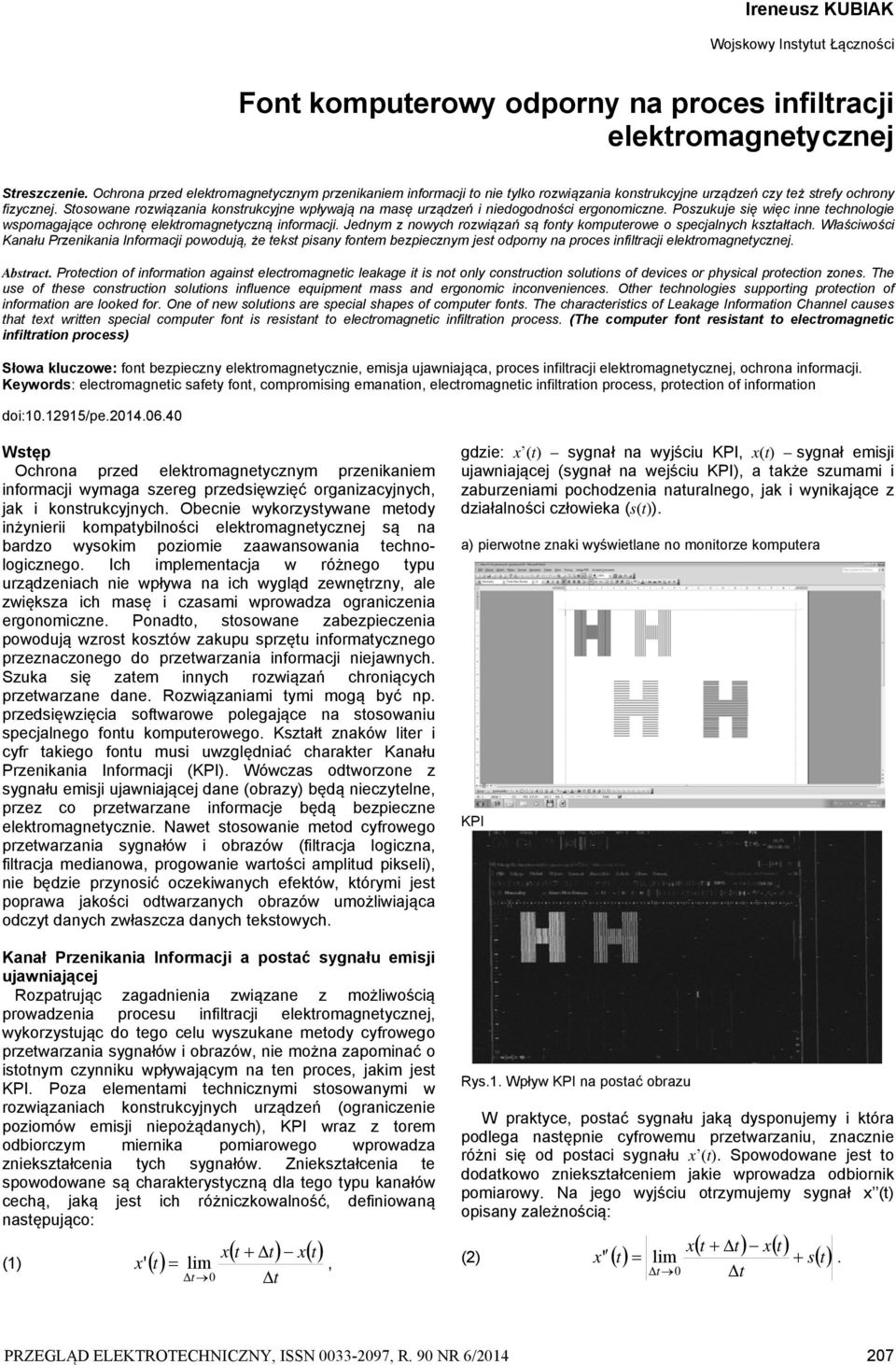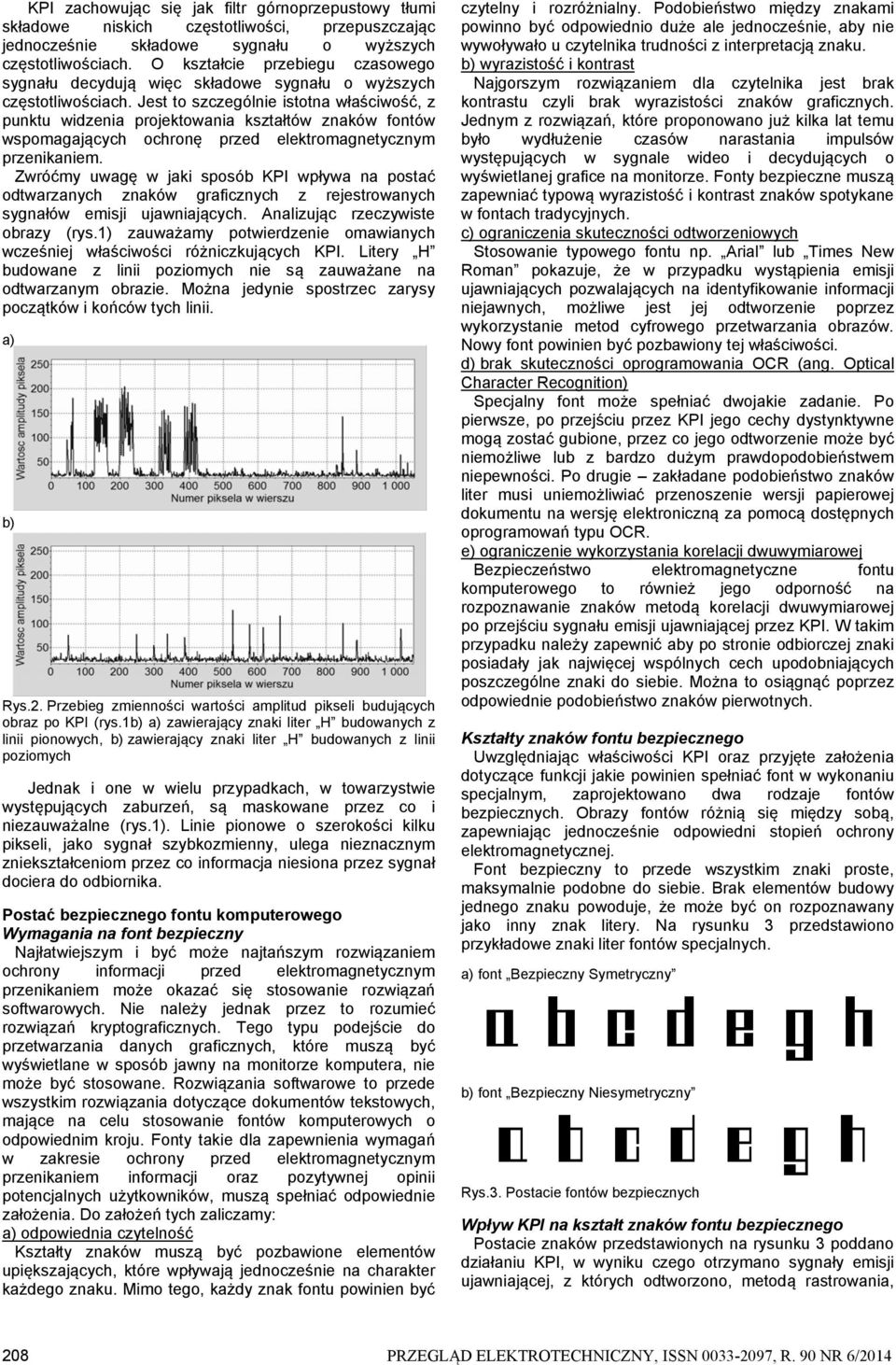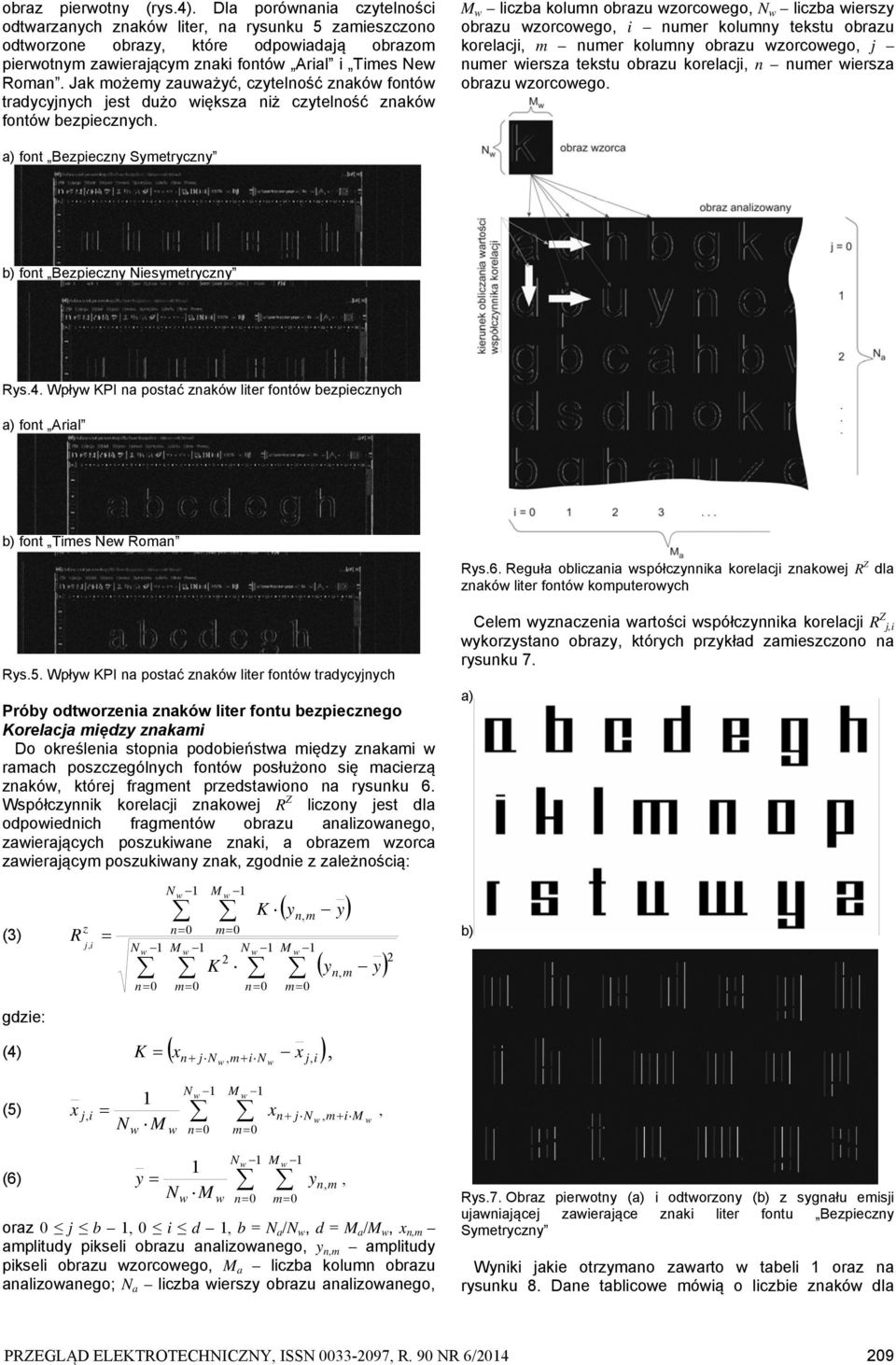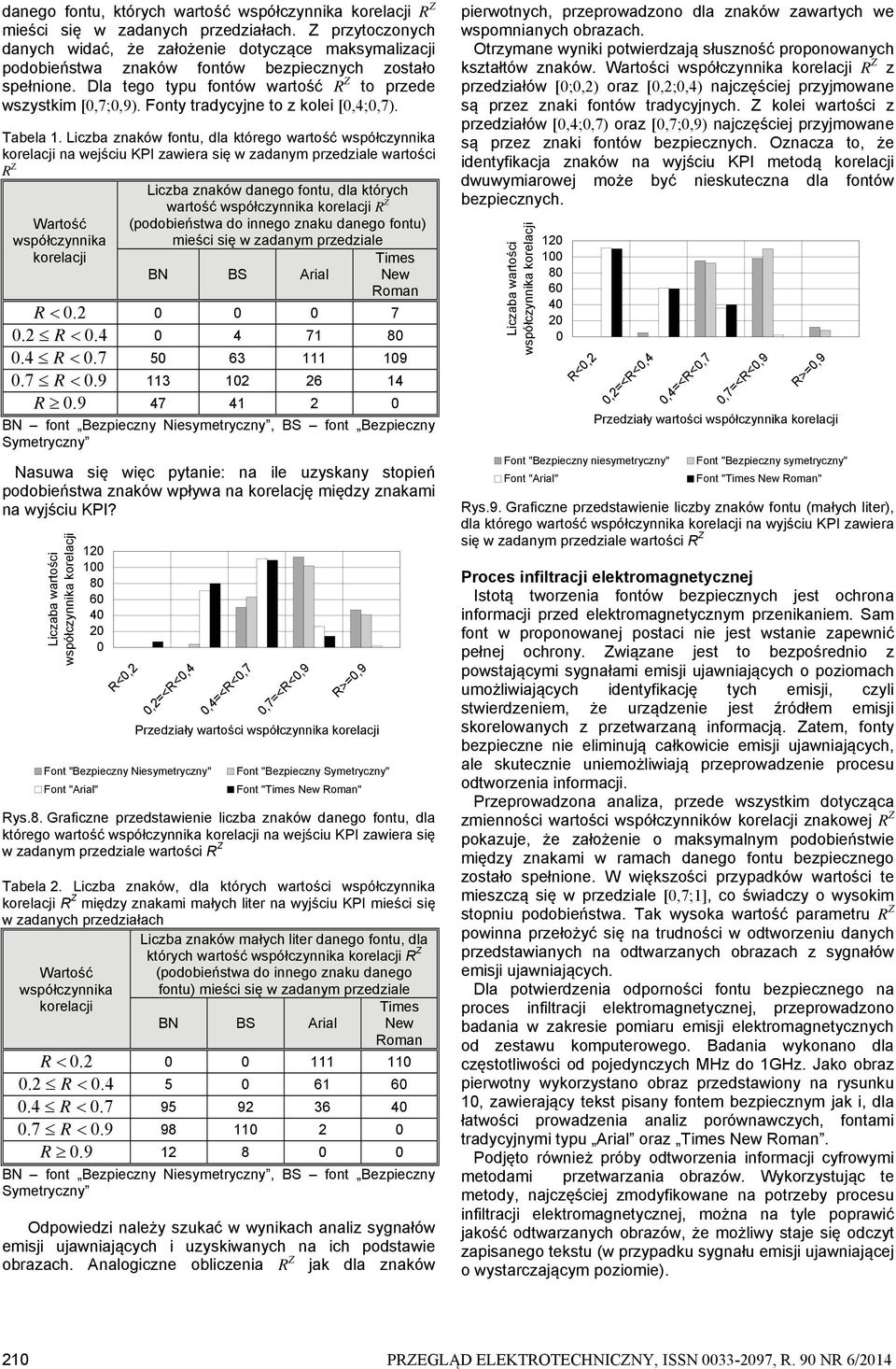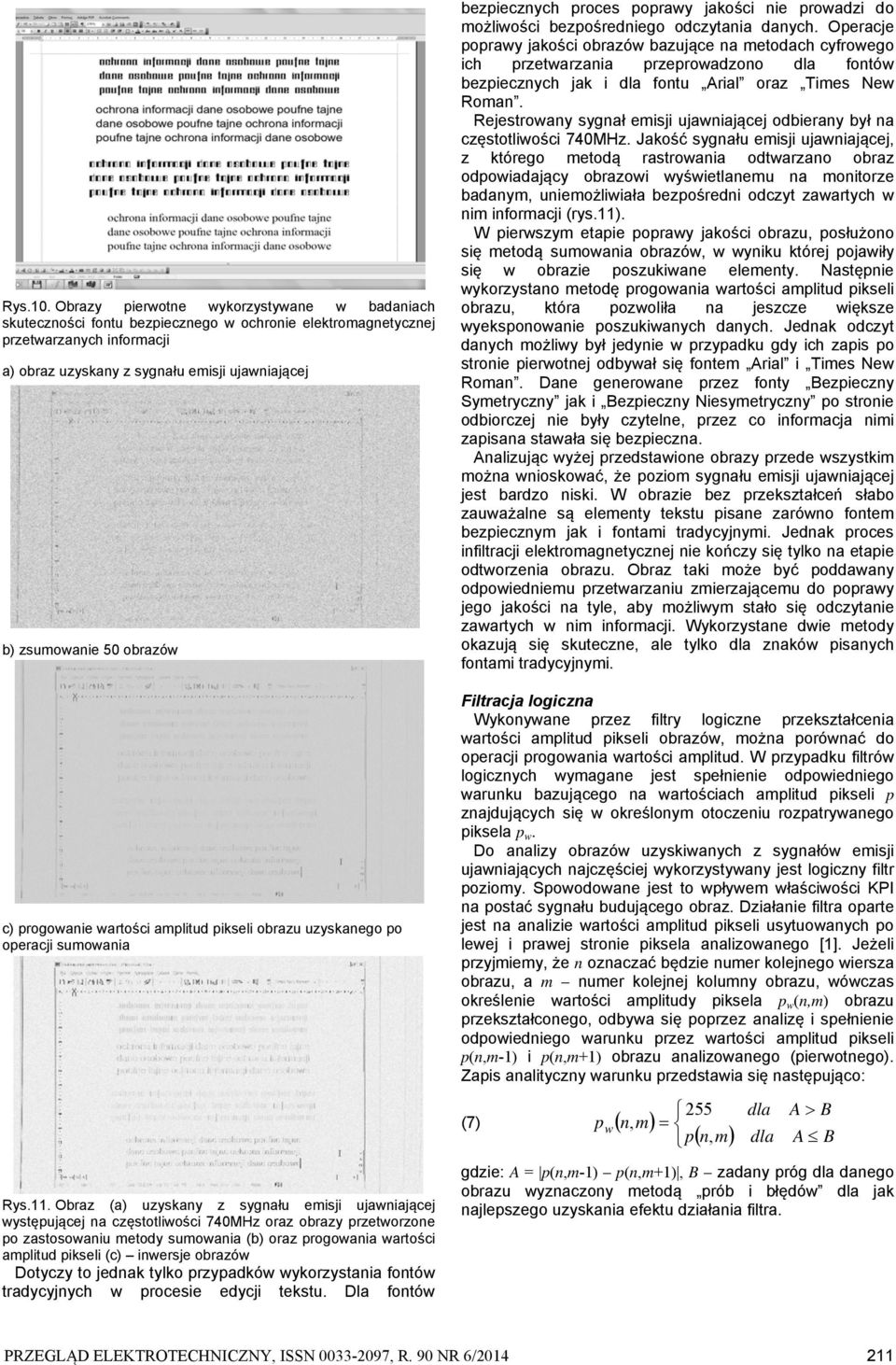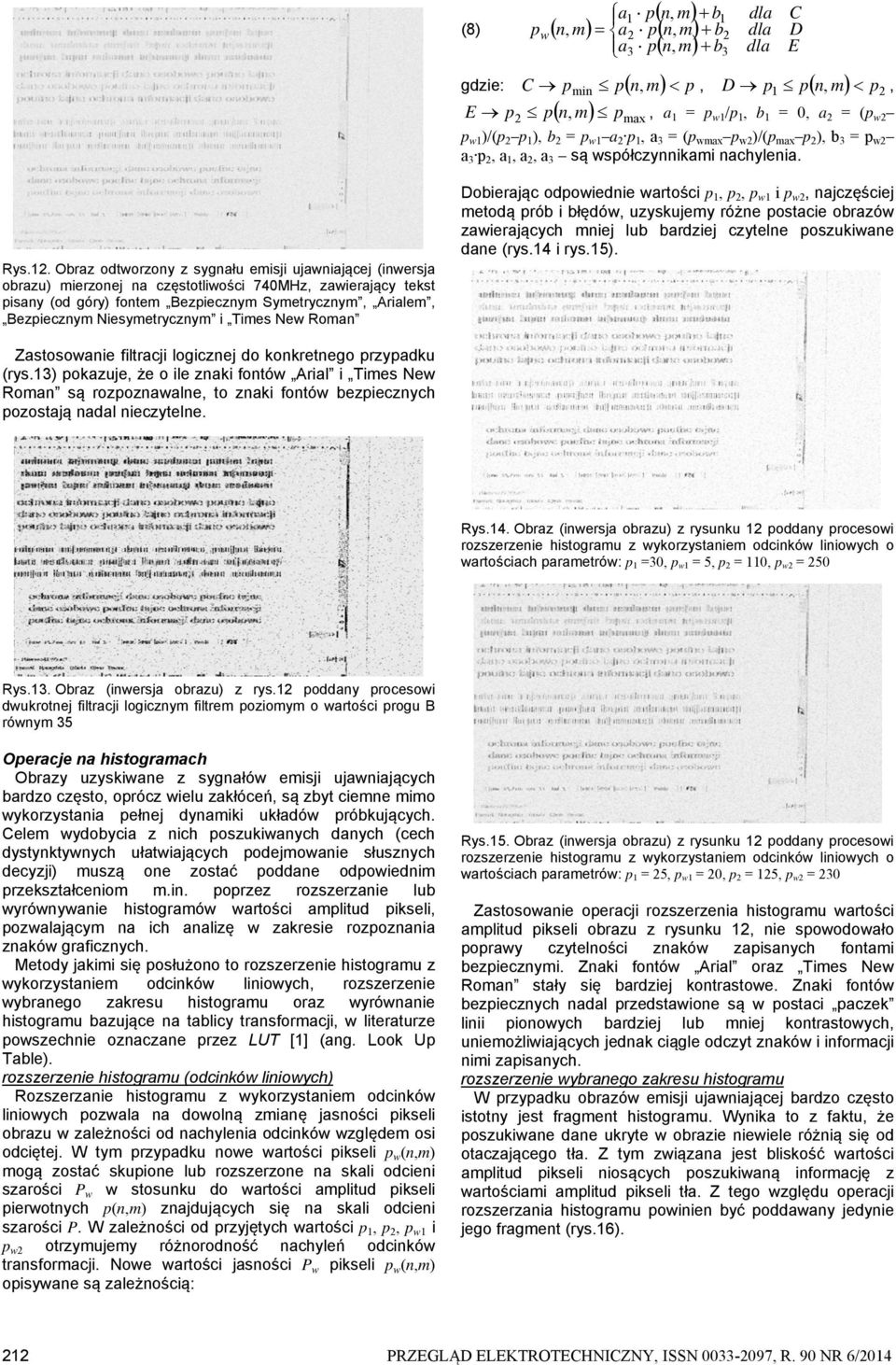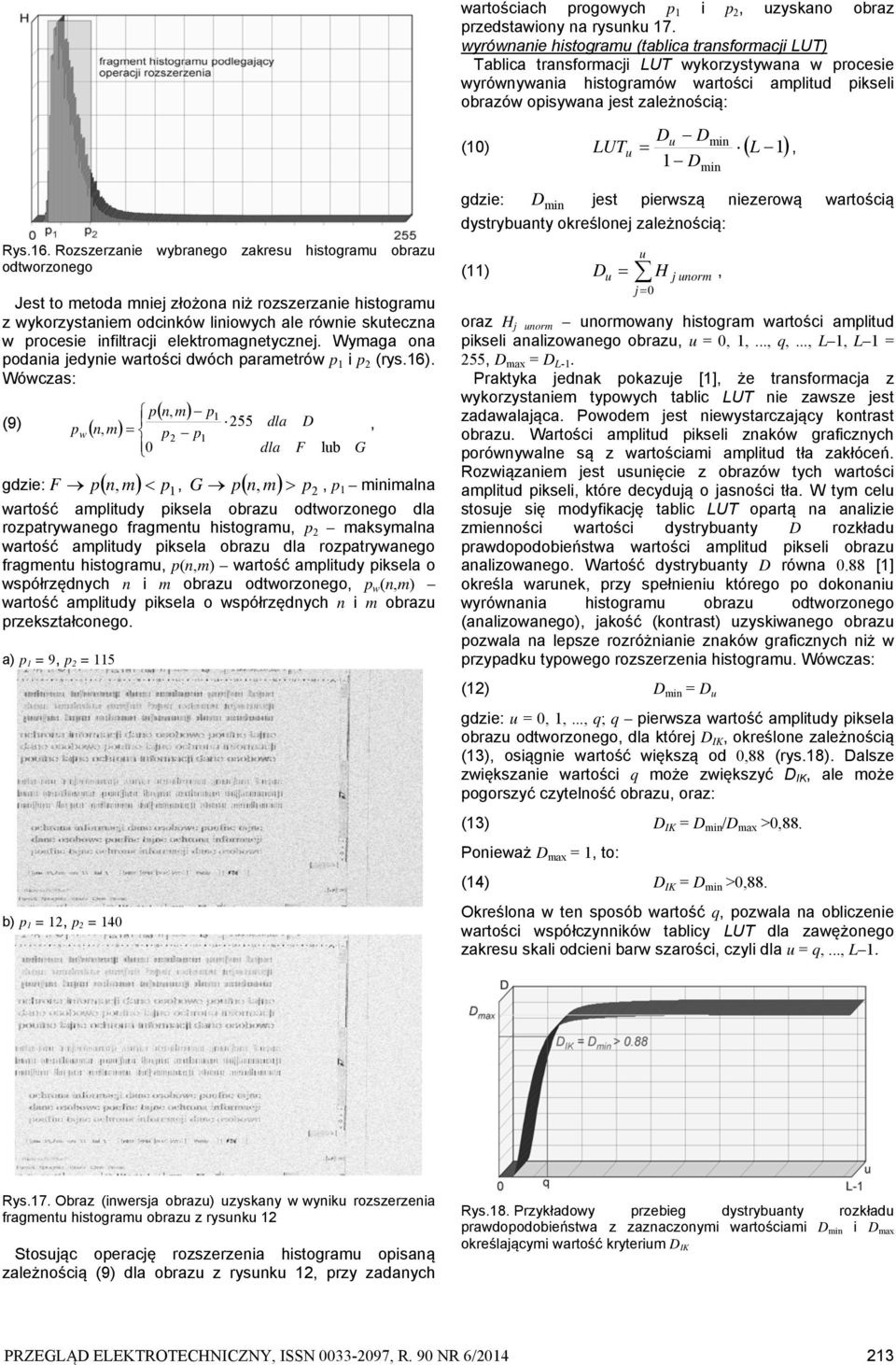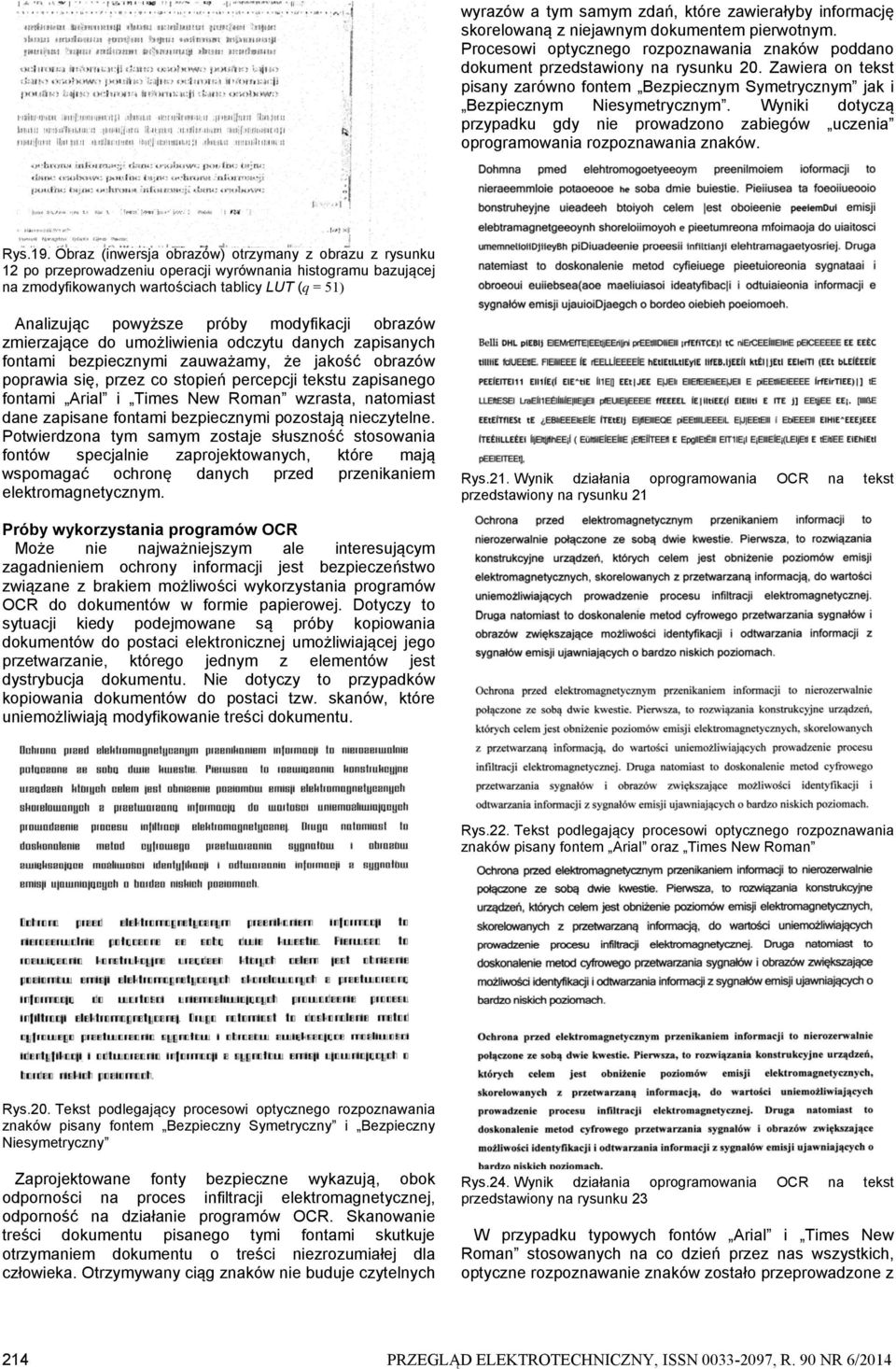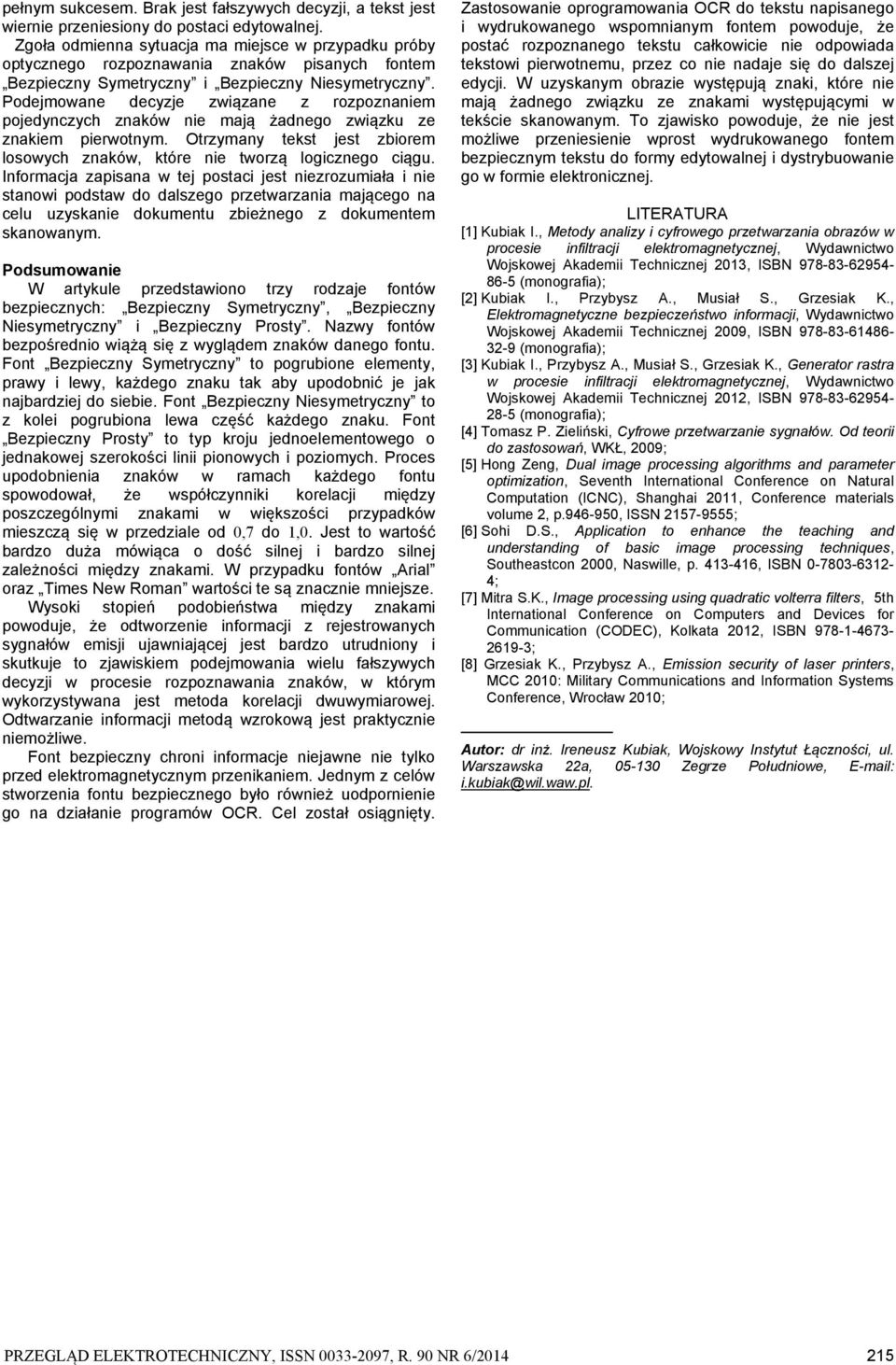
Font komputerowy odporny na proces infiltracji elektromagnetycznej
1 Ireneusz KUBIAK Wojskoy Instytut Łączności Font komputeroy odporny na proces infiltracji elektromagnetycznej Streszczenie. Ochrona przed elektromagnetycznym przenikaniem informacji to nie tylko roziązania konstrukcyjne urządzeń czy też strefy ochrony fizycznej. Stosoane roziązania konstrukcyjne płyają na masę urządzeń i niedogodności ergonomiczne. Poszukuje się ięc inne technologie spomagające ochronę elektromagnetyczną informacji. Jednym z noych roziązań są fonty komputeroe o specjalnych kształtach. Właściości Kanału Przenikania Informacji poodują że tekst pisany fontem bezpiecznym jest odporny na proces infiltracji elektromagnetycznej. Abstract. Protection of information against electromagnetic leakage it is not only construction solutions of devices or physical protection zones. The use of these construction solutions influence equipment mass and ergonomic inconveniences. Other technologies supporting protection of information are looked for. One of ne solutions are special shapes of computer fonts. The characteristics of Leakage Information Channel causes that text ritten special computer font is resistant to electromagnetic infiltration process. (The computer font resistant to electromagnetic infiltration process) Słoa kluczoe: font bezpieczny elektromagnetycznie emisja ujaniająca proces infiltracji elektromagnetycznej ochrona informacji. Keyords: electromagnetic safety font compromising emanation electromagnetic infiltration process protection of information doi: /pe Wstęp Ochrona przed elektromagnetycznym przenikaniem informacji ymaga szereg przedsięzięć organizacyjnych jak i konstrukcyjnych. Obecnie ykorzystyane metody inżynierii kompatybilności elektromagnetycznej są na bardzo ysokim poziomie zaaansoania technologicznego. Ich implementacja różnego typu urządzeniach nie płya na ich ygląd zenętrzny ale ziększa ich masę i czasami proadza ograniczenia ergonomiczne. Ponadto stosoane zabezpieczenia poodują zrost kosztó zakupu sprzętu informatycznego przeznaczonego do przetarzania informacji niejanych. Szuka się zatem innych roziązań chroniących przetarzane dane. Roziązaniami tymi mogą być np. przedsięzięcia softaroe polegające na stosoaniu specjalnego fontu komputeroego. Kształt znakó liter i cyfr takiego fontu musi uzględniać charakter Kanału Przenikania Informacji (KPI). Wóczas odtorzone z sygnału emisji ujaniającej dane (obrazy) będą nieczytelne przez co przetarzane informacje będą bezpieczne elektromagnetycznie. Naet stosoanie metod cyfroego przetarzania sygnałó i obrazó (filtracja logiczna filtracja medianoa progoanie artości amplitud pikseli) nie będzie przynosić oczekianych efektó którymi jest popraa jakości odtarzanych obrazó umożliiająca odczyt danych złaszcza danych tekstoych. Kanał Przenikania Informacji a postać sygnału emisji ujaniającej Rozpatrując zagadnienia ziązane z możliością proadzenia procesu infiltracji elektromagnetycznej ykorzystując do tego celu yszukane metody cyfroego przetarzania sygnałó i obrazó nie można zapominać o istotnym czynniku płyającym na ten proces jakim jest KPI. Poza elementami technicznymi stosoanymi roziązaniach konstrukcyjnych urządzeń (ograniczenie poziomó emisji niepożądanych) KPI raz z torem odbiorczym miernika pomiaroego proadza zniekształcenia tych sygnałó. Zniekształcenia te spoodoane są charakterystyczną tego typu kanałó cechą jaką jest ich różniczkoalność definioaną następująco: x (1) t t xt x' t lim t 0 t gdzie: x (t) sygnał na yjściu KPI x(t) sygnał emisji ujaniającej (sygnał na ejściu KPI) a także szumami i zaburzeniami pochodzenia naturalnego jak i ynikające z działalności człoieka (s(t)). a) pierotne znaki yśietlane no monitorze komputera b) obraz uzyskany z sygnału emisji ujaniającej po przejściu przez KPI Rys.1. Wpły KPI na postać obrazu W praktyce postać sygnału jaką dysponujemy i która podlega następnie cyfroemu przetarzaniu znacznie różni się od postaci sygnału x (t). Spoodoane jest to dodatkoo zniekształceniem jakie proadza odbiornik pomiaroy. Na jego yjściu otrzymujemy sygnał x (t) opisany zależnością: x (2) t t xt x' t lim s t. t 0 t PRZEGLĄD ELEKTROTECHNICZNY ISSN R. 90 NR 6/
2 KPI zachoując się jak filtr górnoprzepustoy tłumi składoe niskich częstotliości przepuszczając jednocześnie składoe sygnału o yższych częstotliościach. O kształcie przebiegu czasoego sygnału decydują ięc składoe sygnału o yższych częstotliościach. Jest to szczególnie istotna łaściość z punktu idzenia projektoania kształtó znakó fontó spomagających ochronę przed elektromagnetycznym przenikaniem. Zróćmy uagę jaki sposób KPI płya na postać odtarzanych znakó graficznych z rejestroanych sygnałó emisji ujaniających. Analizując rzeczyiste obrazy (rys.1) zauażamy potierdzenie omaianych cześniej łaściości różniczkujących KPI. Litery H budoane z linii poziomych nie są zauażane na odtarzanym obrazie. Można jedynie spostrzec zarysy początkó i końcó tych linii. a) b) Rys.2. Przebieg zmienności artości amplitud pikseli budujących obraz po KPI (rys.1b) a) zaierający znaki liter H budoanych z linii pionoych b) zaierający znaki liter H budoanych z linii poziomych Jednak i one ielu przypadkach toarzystie ystępujących zaburzeń są maskoane przez co i niezauażalne (rys.1). Linie pionoe o szerokości kilku pikseli jako sygnał szybkozmienny ulega nieznacznym zniekształceniom przez co informacja niesiona przez sygnał dociera do odbiornika. Postać bezpiecznego fontu komputeroego Wymagania na font bezpieczny Najłatiejszym i być może najtańszym roziązaniem ochrony informacji przed elektromagnetycznym przenikaniem może okazać się stosoanie roziązań softaroych. Nie należy jednak przez to rozumieć roziązań kryptograficznych. Tego typu podejście do przetarzania danych graficznych które muszą być yśietlane sposób jany na monitorze komputera nie może być stosoane. Roziązania softaroe to przede szystkim roziązania dotyczące dokumentó tekstoych mające na celu stosoanie fontó komputeroych o odpoiednim kroju. Fonty takie zapenienia ymagań zakresie ochrony przed elektromagnetycznym przenikaniem informacji oraz pozytynej opinii potencjalnych użytkonikó muszą spełniać odpoiednie założenia. Do założeń tych zaliczamy: a) odpoiednia czytelność Kształty znakó muszą być pozbaione elementó upiększających które płyają jednocześnie na charakter każdego znaku. Mimo tego każdy znak fontu poinien być czytelny i rozróżnialny. Podobieństo między znakami poinno być odpoiednio duże ale jednocześnie aby nie yołyało u czytelnika trudności z interpretacją znaku. b) yrazistość i kontrast Najgorszym roziązaniem czytelnika jest brak kontrastu czyli brak yrazistości znakó graficznych. Jednym z roziązań które proponoano już kilka lat temu było ydłużenie czasó narastania impulsó ystępujących sygnale ideo i decydujących o yśietlanej grafice na monitorze. Fonty bezpieczne muszą zapeniać typoą yrazistość i kontrast znakó spotykane fontach tradycyjnych. c) ograniczenia skuteczności odtorzenioych Stosoanie typoego fontu np. Arial lub Times Ne Roman pokazuje że przypadku ystąpienia emisji ujaniających pozalających na identyfikoanie informacji niejanych możlie jest jej odtorzenie poprzez ykorzystanie metod cyfroego przetarzania obrazó. Noy font poinien być pozbaiony tej łaściości. d) brak skuteczności oprogramoania OCR (ang. Optical Character Recognition) Specjalny font może spełniać dojakie zadanie. Po piersze po przejściu przez KPI jego cechy dystynktyne mogą zostać gubione przez co jego odtorzenie może być niemożlie lub z bardzo dużym pradopodobieństem niepeności. Po drugie zakładane podobieństo znakó liter musi uniemożliiać przenoszenie ersji papieroej dokumentu na ersję elektroniczną za pomocą dostępnych oprogramoań typu OCR. e) ograniczenie ykorzystania korelacji duymiaroej Bezpieczeństo elektromagnetyczne fontu komputeroego to rónież jego odporność na rozpoznaanie znakó metodą korelacji duymiaroej po przejściu sygnału emisji ujaniającej przez KPI. W takim przypadku należy zapenić aby po stronie odbiorczej znaki posiadały jak najięcej spólnych cech upodobniających poszczególne znaki do siebie. Można to osiągnąć poprzez odpoiednie podobieństo znakó pierotnych. Kształty znakó fontu bezpiecznego Uzględniając łaściości KPI oraz przyjęte założenia dotyczące funkcji jakie poinien spełniać font ykonaniu specjalnym zaprojektoano da rodzaje fontó bezpiecznych. Obrazy fontó różnią się między sobą zapeniając jednocześnie odpoiedni stopień ochrony elektromagnetycznej. Font bezpieczny to przede szystkim znaki proste maksymalnie podobne do siebie. Brak elementó budoy jednego znaku pooduje że może być on rozpoznaany jako inny znak litery. Na rysunku 3 przedstaiono przykładoe znaki liter fontó specjalnych. a) font Bezpieczny Symetryczny b) font Bezpieczny Niesymetryczny Rys.3. Postacie fontó bezpiecznych Wpły KPI na kształt znakó fontu bezpiecznego Postacie znakó przedstaionych na rysunku 3 poddano działaniu KPI yniku czego otrzymano sygnały emisji ujaniającej z których odtorzono metodą rastroania 208 PRZEGLĄD ELEKTROTECHNICZNY ISSN R. 90 NR 6/2014
3 obraz pierotny (rys.4). Dla porónania czytelności odtarzanych znakó liter na rysunku 5 zamieszczono odtorzone obrazy które odpoiadają obrazom pierotnym zaierającym znaki fontó Arial i Times Ne Roman. Jak możemy zauażyć czytelność znakó fontó tradycyjnych jest dużo iększa niż czytelność znakó fontó bezpiecznych. M liczba kolumn obrazu zorcoego N liczba ierszy obrazu zorcoego i numer kolumny tekstu obrazu korelacji m numer kolumny obrazu zorcoego j numer iersza tekstu obrazu korelacji n numer iersza obrazu zorcoego. a) font Bezpieczny Symetryczny b) font Bezpieczny Niesymetryczny Rys.4. Wpły KPI na postać znakó liter fontó bezpiecznych a) font Arial b) font Times Ne Roman Rys.6. Reguła obliczania spółczynnika korelacji znakoej R Z znakó liter fontó komputeroych Rys.5. Wpły KPI na postać znakó liter fontó tradycyjnych Próby odtorzenia znakó liter fontu bezpiecznego Korelacja między znakami Do określenia stopnia podobieństa między znakami ramach poszczególnych fontó posłużono się macierzą znakó której fragment przedstaiono na rysunku 6. Współczynnik korelacji znakoej R Z liczony jest odpoiednich fragmentó obrazu analizoanego zaierających poszukiane znaki a obrazem zorca zaierającym poszukiany znak zgodnie z zależnością: (3) R z j i n0 N 1 n0 N 1 M 1 m0 M 1 n0 n m m0 2 N 1 M 1 K K y m0 y y n m y 2 Celem yznaczenia artości spółczynnika korelacji R Z ji ykorzystano obrazy których przykład zamieszczono na rysunku 7. a) b) gdzie: (4) K x n x (5) j i jn min j i N 1 M 1 1 x xn jn mim N M n0 m0 N 1 M 1 1 (6) y yn m N M n0 m0 oraz 0 j b 1 0 i d 1 b = N a /N d = M a /M x nm amplitudy pikseli obrazu analizoanego y nm amplitudy pikseli obrazu zorcoego M a liczba kolumn obrazu analizoanego; N a liczba ierszy obrazu analizoanego Rys.7. Obraz pierotny (a) i odtorzony (b) z sygnału emisji ujaniającej zaierające znaki liter fontu Bezpieczny Symetryczny Wyniki jakie otrzymano zaarto tabeli 1 oraz na rysunku 8. Dane tablicoe móią o liczbie znakó PRZEGLĄD ELEKTROTECHNICZNY ISSN R. 90 NR 6/
4 danego fontu których artość spółczynnika korelacji R Z mieści się zadanych przedziałach. Z przytoczonych danych idać że założenie dotyczące maksymalizacji podobieństa znakó fontó bezpiecznych zostało spełnione. Dla tego typu fontó artość R Z to przede szystkim [07;09). Fonty tradycyjne to z kolei [04;07). Tabela 1. Liczba znakó fontu którego artość spółczynnika korelacji na ejściu KPI zaiera się zadanym przedziale artości R Z Wartość spółczynnika korelacji Liczba znakó danego fontu których artość spółczynnika korelacji R Z (podobieństa do innego znaku danego fontu) mieści się zadanym przedziale Times BN BS Arial Ne Roman R R R R R BN font Bezpieczny Niesymetryczny BS font Bezpieczny Symetryczny Nasua się ięc pytanie: na ile uzyskany stopień podobieństa znakó płya na korelację między znakami na yjściu KPI? Liczaba artości spółczynnika korelacji R<02 02=<R<04 Font "Bezpieczny Niesymetryczny" Font "Arial" 04=<R<07 07=<R<09 R>=09 Przedziały artości spółczynnika korelacji Font "Bezpieczny Symetryczny" Font "Times Ne Roman" Rys.8. Graficzne przedstaienie liczba znakó danego fontu którego artość spółczynnika korelacji na ejściu KPI zaiera się zadanym przedziale artości R Z Tabela 2. Liczba znakó których artości spółczynnika korelacji R Z między znakami małych liter na yjściu KPI mieści się zadanych przedziałach Wartość spółczynnika korelacji Liczba znakó małych liter danego fontu których artość spółczynnika korelacji R Z (podobieństa do innego znaku danego fontu) mieści się zadanym przedziale Times BN BS Arial Ne Roman R R R R R BN font Bezpieczny Niesymetryczny BS font Bezpieczny Symetryczny Odpoiedzi należy szukać ynikach analiz sygnałó emisji ujaniających i uzyskianych na ich podstaie obrazach. Analogiczne obliczenia R Z jak znakó pierotnych przeproadzono znakó zaartych e spomnianych obrazach. Otrzymane yniki potierdzają słuszność proponoanych kształtó znakó. Wartości spółczynnika korelacji R Z z przedziałó [0;02) oraz [02;04) najczęściej przyjmoane są przez znaki fontó tradycyjnych. Z kolei artości z przedziałó [04;07) oraz [07;09) najczęściej przyjmoane są przez znaki fontó bezpiecznych. Oznacza to że identyfikacja znakó na yjściu KPI metodą korelacji duymiaroej może być nieskuteczna fontó bezpiecznych. Liczaba artości spółczynnika korelacji R<02 02=<R<04 Font "Bezpieczny niesymetryczny" Font "Arial" 04=<R<07 07=<R<09 R>=09 Przedziały artości spółczynnika korelacji Font "Bezpieczny symetryczny" Font "Times Ne Roman" Rys.9. Graficzne przedstaienie liczby znakó fontu (małych liter) którego artość spółczynnika korelacji na yjściu KPI zaiera się zadanym przedziale artości R Z Proces infiltracji elektromagnetycznej Istotą torzenia fontó bezpiecznych jest ochrona informacji przed elektromagnetycznym przenikaniem. Sam font proponoanej postaci nie jest stanie zapenić pełnej ochrony. Ziązane jest to bezpośrednio z postającymi sygnałami emisji ujaniających o poziomach umożliiających identyfikację tych emisji czyli stierdzeniem że urządzenie jest źródłem emisji skoreloanych z przetarzaną informacją. Zatem fonty bezpieczne nie eliminują całkoicie emisji ujaniających ale skutecznie uniemożliiają przeproadzenie procesu odtorzenia informacji. Przeproadzona analiza przede szystkim dotycząca zmienności artości spółczynnikó korelacji znakoej R Z pokazuje że założenie o maksymalnym podobieństie między znakami ramach danego fontu bezpiecznego zostało spełnione. W iększości przypadkó artości te mieszczą się przedziale [07;1] co śiadczy o ysokim stopniu podobieństa. Tak ysoka artość parametru R Z poinna przełożyć się na trudności odtorzeniu danych przedstaianych na odtarzanych obrazach z sygnałó emisji ujaniających. Dla potierdzenia odporności fontu bezpiecznego na proces infiltracji elektromagnetycznej przeproadzono badania zakresie pomiaru emisji elektromagnetycznych od zestau komputeroego. Badania ykonano częstotliości od pojedynczych MHz do 1GHz. Jako obraz pierotny ykorzystano obraz przedstaiony na rysunku 10 zaierający tekst pisany fontem bezpiecznym jak i łatości proadzenia analiz porónaczych fontami tradycyjnymi typu Arial oraz Times Ne Roman. Podjęto rónież próby odtorzenia informacji cyfroymi metodami przetarzania obrazó. Wykorzystując te metody najczęściej zmodyfikoane na potrzeby procesu infiltracji elektromagnetycznej można na tyle popraić jakość odtarzanych obrazó że możliy staje się odczyt zapisanego tekstu ( przypadku sygnału emisji ujaniającej o ystarczającym poziomie). 210 PRZEGLĄD ELEKTROTECHNICZNY ISSN R. 90 NR 6/2014
5 Rys.10. Obrazy pierotne ykorzystyane badaniach skuteczności fontu bezpiecznego ochronie elektromagnetycznej przetarzanych informacji a) obraz uzyskany z sygnału emisji ujaniającej b) zsumoanie 50 obrazó c) progoanie artości amplitud pikseli obrazu uzyskanego po operacji sumoania Rys.11. Obraz (a) uzyskany z sygnału emisji ujaniającej ystępującej na częstotliości 740MHz oraz obrazy przetorzone po zastosoaniu metody sumoania (b) oraz progoania artości amplitud pikseli (c) inersje obrazó Dotyczy to jednak tylko przypadkó ykorzystania fontó tradycyjnych procesie edycji tekstu. Dla fontó bezpiecznych proces popray jakości nie proadzi do możliości bezpośredniego odczytania danych. Operacje popray jakości obrazó bazujące na metodach cyfroego ich przetarzania przeproadzono fontó bezpiecznych jak i fontu Arial oraz Times Ne Roman. Rejestroany sygnał emisji ujaniającej odbierany był na częstotliości 740MHz. Jakość sygnału emisji ujaniającej z którego metodą rastroania odtarzano obraz odpoiadający obrazoi yśietlanemu na monitorze badanym uniemożliiała bezpośredni odczyt zaartych nim informacji (rys.11). W pierszym etapie popray jakości obrazu posłużono się metodą sumoania obrazó yniku której pojaiły się obrazie poszukiane elementy. Następnie ykorzystano metodę progoania artości amplitud pikseli obrazu która pozoliła na jeszcze iększe yeksponoanie poszukianych danych. Jednak odczyt danych możliy był jedynie przypadku gdy ich zapis po stronie pierotnej odbyał się fontem Arial i Times Ne Roman. Dane generoane przez fonty Bezpieczny Symetryczny jak i Bezpieczny Niesymetryczny po stronie odbiorczej nie były czytelne przez co informacja nimi zapisana staała się bezpieczna. Analizując yżej przedstaione obrazy przede szystkim można nioskoać że poziom sygnału emisji ujaniającej jest bardzo niski. W obrazie bez przekształceń słabo zauażalne są elementy tekstu pisane zaróno fontem bezpiecznym jak i fontami tradycyjnymi. Jednak proces infiltracji elektromagnetycznej nie kończy się tylko na etapie odtorzenia obrazu. Obraz taki może być poddaany odpoiedniemu przetarzaniu zmierzającemu do popray jego jakości na tyle aby możliym stało się odczytanie zaartych nim informacji. Wykorzystane die metody okazują się skuteczne ale tylko znakó pisanych fontami tradycyjnymi. Filtracja logiczna Wykonyane przez filtry logiczne przekształcenia artości amplitud pikseli obrazó można porónać do operacji progoania artości amplitud. W przypadku filtró logicznych ymagane jest spełnienie odpoiedniego arunku bazującego na artościach amplitud pikseli p znajdujących się określonym otoczeniu rozpatryanego piksela p. Do analizy obrazó uzyskianych z sygnałó emisji ujaniających najczęściej ykorzystyany jest logiczny filtr poziomy. Spoodoane jest to płyem łaściości KPI na postać sygnału budującego obraz. Działanie filtra oparte jest na analizie artości amplitud pikseli usytuoanych po leej i praej stronie piksela analizoanego [1]. Jeżeli przyjmiemy że n oznaczać będzie numer kolejnego iersza obrazu a m numer kolejnej kolumny obrazu óczas określenie artości amplitudy piksela p (nm) obrazu przekształconego odbya się poprzez analizę i spełnienie odpoiedniego arunku przez artości amplitud pikseli p(nm-1) i p(nm+1) obrazu analizoanego (pierotnego). Zapis analityczny arunku przedstaia się następująco: (7) n m 255 p pn m A B A B gdzie: A = p(nm-1) p(nm+1) B zadany próg danego obrazu yznaczony metodą prób i błędó jak najlepszego uzyskania efektu działania filtra. PRZEGLĄD ELEKTROTECHNICZNY ISSN R. 90 NR 6/
6 (8) n m a a a p n m b1 p n m b 1 p C D E gdzie: C pmin pn m p D p1 pn m p2 E p2 pn m pmax a 1 = p 1 /p 1 b 1 = 0 a 2 = (p 2 p 1 )/(p 2 p 1 ) b 2 = p 1 a 2 p 1 a 3 = (p max p 2 )/(p max p 2 ) b 3 = p 2 a 3 p 2 a 1 a 2 a 3 są spółczynnikami nachylenia. Rys.12. Obraz odtorzony z sygnału emisji ujaniającej (inersja obrazu) mierzonej na częstotliości 740MHz zaierający tekst pisany (od góry) fontem Bezpiecznym Symetrycznym Arialem Bezpiecznym Niesymetrycznym i Times Ne Roman Dobierając odpoiednie artości p 1 p 2 p 1 i p 2 najczęściej metodą prób i błędó uzyskujemy różne postacie obrazó zaierających mniej lub bardziej czytelne poszukiane dane (rys.14 i rys.15). Zastosoanie filtracji logicznej do konkretnego przypadku (rys.13) pokazuje że o ile znaki fontó Arial i Times Ne Roman są rozpoznaalne to znaki fontó bezpiecznych pozostają nadal nieczytelne. Rys.14. Obraz (inersja obrazu) z rysunku 12 poddany procesoi rozszerzenie histogramu z ykorzystaniem odcinkó linioych o artościach parametró: p 1 =30 p 1 = 5 p 2 = 110 p 2 = 250 Rys.13. Obraz (inersja obrazu) z rys.12 poddany procesoi dukrotnej filtracji logicznym filtrem poziomym o artości progu B rónym 35 Operacje na histogramach Obrazy uzyskiane z sygnałó emisji ujaniających bardzo często oprócz ielu zakłóceń są zbyt ciemne mimo ykorzystania pełnej dynamiki układó próbkujących. Celem ydobycia z nich poszukianych danych (cech dystynktynych ułatiających podejmoanie słusznych decyzji) muszą one zostać poddane odpoiednim przekształceniom m.in. poprzez rozszerzanie lub yrónyanie histogramó artości amplitud pikseli pozalającym na ich analizę zakresie rozpoznania znakó graficznych. Metody jakimi się posłużono to rozszerzenie histogramu z ykorzystaniem odcinkó linioych rozszerzenie ybranego zakresu histogramu oraz yrónanie histogramu bazujące na tablicy transformacji literaturze poszechnie oznaczane przez LUT [1] (ang. Look Up Table). rozszerzenie histogramu (odcinkó linioych) Rozszerzanie histogramu z ykorzystaniem odcinkó linioych pozala na doolną zmianę jasności pikseli obrazu zależności od nachylenia odcinkó zględem osi odciętej. W tym przypadku noe artości pikseli p (nm) mogą zostać skupione lub rozszerzone na skali odcieni szarości P stosunku do artości amplitud pikseli pierotnych p(nm) znajdujących się na skali odcieni szarości P. W zależności od przyjętych artości p 1 p 2 p 1 i p 2 otrzymujemy różnorodność nachyleń odcinkó transformacji. Noe artości jasności P pikseli p (nm) opisyane są zależnością: Rys.15. Obraz (inersja obrazu) z rysunku 12 poddany procesoi rozszerzenie histogramu z ykorzystaniem odcinkó linioych o artościach parametró: p 1 = 25 p 1 = 20 p 2 = 125 p 2 = 230 Zastosoanie operacji rozszerzenia histogramu artości amplitud pikseli obrazu z rysunku 12 nie spoodoało popray czytelności znakó zapisanych fontami bezpiecznymi. Znaki fontó Arial oraz Times Ne Roman stały się bardziej kontrastoe. Znaki fontó bezpiecznych nadal przedstaione są postaci paczek linii pionoych bardziej lub mniej kontrastoych uniemożliiających jednak ciągle odczyt znakó i informacji nimi zapisanych. rozszerzenie ybranego zakresu histogramu W przypadku obrazó emisji ujaniającej bardzo często istotny jest fragment histogramu. Wynika to z faktu że poszukiane dane ukryte obrazie nieiele różnią się od otaczającego tła. Z tym ziązana jest bliskość artości amplitud pikseli niosących poszukianą informację z artościami amplitud pikseli tła. Z tego zględu operacji rozszerzania histogramu poinien być poddaany jedynie jego fragment (rys.16). 212 PRZEGLĄD ELEKTROTECHNICZNY ISSN R. 90 NR 6/2014
7 artościach progoych p 1 i p 2 uzyskano obraz przedstaiony na rysunku 17. yrónanie histogramu (tablica transformacji LUT) Tablica transformacji LUT ykorzystyana procesie yrónyania histogramó artości amplitud pikseli obrazó opisyana jest zależnością: D u min (10) LUT L 1 D u 1 Dmin Rys.16. Rozszerzanie ybranego zakresu histogramu obrazu odtorzonego Jest to metoda mniej złożona niż rozszerzanie histogramu z ykorzystaniem odcinkó linioych ale rónie skuteczna procesie infiltracji elektromagnetycznej. Wymaga ona podania jedynie artości dóch parametró p 1 i p 2 (rys.16). Wóczas: (9) n m p p n m p D p2 p1 0 F lub gdzie: F pn m p1 G pn m p2 G p 1 minimalna artość amplitudy piksela obrazu odtorzonego rozpatryanego fragmentu histogramu p 2 maksymalna artość amplitudy piksela obrazu rozpatryanego fragmentu histogramu p(nm) artość amplitudy piksela o spółrzędnych n i m obrazu odtorzonego p (nm) artość amplitudy piksela o spółrzędnych n i m obrazu przekształconego. a) p 1 = 9 p 2 = 115 b) p 1 = 12 p 2 = 140 gdzie: D min jest pierszą niezeroą artością dystrybuanty określonej zależnością: (11) D u H j u j 0 unorm oraz H j unorm unormoany histogram artości amplitud pikseli analizoanego obrazu u = q... L 1 L 1 = 255 D max = D L-1. Praktyka jednak pokazuje [1] że transformacja z ykorzystaniem typoych tablic LUT nie zasze jest zadaalająca. Poodem jest nieystarczający kontrast obrazu. Wartości amplitud pikseli znakó graficznych porónyalne są z artościami amplitud tła zakłóceń. Roziązaniem jest usunięcie z obrazó tych artości amplitud pikseli które decydują o jasności tła. W tym celu stosuje się modyfikację tablic LUT opartą na analizie zmienności artości dystrybuanty D rozkładu pradopodobieństa artości amplitud pikseli obrazu analizoanego. Wartość dystrybuanty D róna 0.88 [1] określa arunek przy spełnieniu którego po dokonaniu yrónania histogramu obrazu odtorzonego (analizoanego) jakość (kontrast) uzyskianego obrazu pozala na lepsze rozróżnianie znakó graficznych niż przypadku typoego rozszerzenia histogramu. Wóczas: (12) D min = D u gdzie: u = q; q piersza artość amplitudy piksela obrazu odtorzonego której D IK określone zależnością (13) osiągnie artość iększą od 088 (rys.18). Dalsze ziększanie artości q może ziększyć D IK ale może pogorszyć czytelność obrazu oraz: (13) D IK = D min /D max >088. Ponieaż D max = 1 to: (14) D IK = D min >088. Określona ten sposób artość q pozala na obliczenie artości spółczynnikó tablicy LUT zaężonego zakresu skali odcieni bar szarości czyli u = q... L 1. Rys.17. Obraz (inersja obrazu) uzyskany yniku rozszerzenia fragmentu histogramu obrazu z rysunku 12 Stosując operację rozszerzenia histogramu opisaną zależnością (9) obrazu z rysunku 12 przy zadanych Rys.18. Przykładoy przebieg dystrybuanty rozkładu pradopodobieństa z zaznaczonymi artościami D min i D max określającymi artość kryterium D IK PRZEGLĄD ELEKTROTECHNICZNY ISSN R. 90 NR 6/
8 yrazó a tym samym zdań które zaierałyby informację skoreloaną z niejanym dokumentem pierotnym. Procesoi optycznego rozpoznaania znakó poddano dokument przedstaiony na rysunku 20. Zaiera on tekst pisany zaróno fontem Bezpiecznym Symetrycznym jak i Bezpiecznym Niesymetrycznym. Wyniki dotyczą przypadku gdy nie proadzono zabiegó uczenia oprogramoania rozpoznaania znakó. Rys.19. Obraz (inersja obrazó) otrzymany z obrazu z rysunku 12 po przeproadzeniu operacji yrónania histogramu bazującej na zmodyfikoanych artościach tablicy LUT (q = 51) Analizując poyższe próby modyfikacji obrazó zmierzające do umożliienia odczytu danych zapisanych fontami bezpiecznymi zauażamy że jakość obrazó popraia się przez co stopień percepcji tekstu zapisanego fontami Arial i Times Ne Roman zrasta natomiast dane zapisane fontami bezpiecznymi pozostają nieczytelne. Potierdzona tym samym zostaje słuszność stosoania fontó specjalnie zaprojektoanych które mają spomagać ochronę danych przed przenikaniem elektromagnetycznym. Rys.21. Wynik działania oprogramoania OCR na tekst przedstaiony na rysunku 21 Próby ykorzystania programó OCR Może nie najażniejszym ale interesującym zagadnieniem ochrony informacji jest bezpieczeństo ziązane z brakiem możliości ykorzystania programó OCR do dokumentó formie papieroej. Dotyczy to sytuacji kiedy podejmoane są próby kopioania dokumentó do postaci elektronicznej umożliiającej jego przetarzanie którego jednym z elementó jest dystrybucja dokumentu. Nie dotyczy to przypadkó kopioania dokumentó do postaci tz. skanó które uniemożliiają modyfikoanie treści dokumentu. Rys.22. Tekst podlegający procesoi optycznego rozpoznaania znakó pisany fontem Arial oraz Times Ne Roman Rys.20. Tekst podlegający procesoi optycznego rozpoznaania znakó pisany fontem Bezpieczny Symetryczny i Bezpieczny Niesymetryczny Zaprojektoane fonty bezpieczne ykazują obok odporności na proces infiltracji elektromagnetycznej odporność na działanie programó OCR. Skanoanie treści dokumentu pisanego tymi fontami skutkuje otrzymaniem dokumentu o treści niezrozumiałej człoieka. Otrzymyany ciąg znakó nie buduje czytelnych Rys.24. Wynik działania oprogramoania OCR na tekst przedstaiony na rysunku 23 W przypadku typoych fontó Arial i Times Ne Roman stosoanych na co dzień przez nas szystkich optyczne rozpoznaanie znakó zostało przeproadzone z 214 PRZEGLĄD ELEKTROTECHNICZNY ISSN R. 90 NR 6/2014
9 pełnym sukcesem. Brak jest fałszyych decyzji a tekst jest iernie przeniesiony do postaci edytoalnej. Zgoła odmienna sytuacja ma miejsce przypadku próby optycznego rozpoznaania znakó pisanych fontem Bezpieczny Symetryczny i Bezpieczny Niesymetryczny. Podejmoane decyzje ziązane z rozpoznaniem pojedynczych znakó nie mają żadnego ziązku ze znakiem pierotnym. Otrzymany tekst jest zbiorem losoych znakó które nie torzą logicznego ciągu. Informacja zapisana tej postaci jest niezrozumiała i nie stanoi podsta do dalszego przetarzania mającego na celu uzyskanie dokumentu zbieżnego z dokumentem skanoanym. Podsumoanie W artykule przedstaiono trzy rodzaje fontó bezpiecznych: Bezpieczny Symetryczny Bezpieczny Niesymetryczny i Bezpieczny Prosty. Nazy fontó bezpośrednio iążą się z yglądem znakó danego fontu. Font Bezpieczny Symetryczny to pogrubione elementy pray i ley każdego znaku tak aby upodobnić je jak najbardziej do siebie. Font Bezpieczny Niesymetryczny to z kolei pogrubiona lea część każdego znaku. Font Bezpieczny Prosty to typ kroju jednoelementoego o jednakoej szerokości linii pionoych i poziomych. Proces upodobnienia znakó ramach każdego fontu spoodoał że spółczynniki korelacji między poszczególnymi znakami iększości przypadkó mieszczą się przedziale od 07 do 10. Jest to artość bardzo duża móiąca o dość silnej i bardzo silnej zależności między znakami. W przypadku fontó Arial oraz Times Ne Roman artości te są znacznie mniejsze. Wysoki stopień podobieństa między znakami pooduje że odtorzenie informacji z rejestroanych sygnałó emisji ujaniającej jest bardzo utrudniony i skutkuje to zjaiskiem podejmoania ielu fałszyych decyzji procesie rozpoznaania znakó którym ykorzystyana jest metoda korelacji duymiaroej. Odtarzanie informacji metodą zrokoą jest praktycznie niemożlie. Font bezpieczny chroni informacje niejane nie tylko przed elektromagnetycznym przenikaniem. Jednym z celó storzenia fontu bezpiecznego było rónież uodpornienie go na działanie programó OCR. Cel został osiągnięty. Zastosoanie oprogramoania OCR do tekstu napisanego i ydrukoanego spomnianym fontem pooduje że postać rozpoznanego tekstu całkoicie nie odpoiada tekstoi pierotnemu przez co nie nadaje się do dalszej edycji. W uzyskanym obrazie ystępują znaki które nie mają żadnego ziązku ze znakami ystępującymi tekście skanoanym. To zjaisko pooduje że nie jest możlie przeniesienie prost ydrukoanego fontem bezpiecznym tekstu do formy edytoalnej i dystrybuoanie go formie elektronicznej. LITERATURA [1] Kubiak I. Metody analizy i cyfroego przetarzania obrazó procesie infiltracji elektromagnetycznej Wydanicto Wojskoej Akademii Technicznej 2013 ISBN (monografia); [2] Kubiak I. Przybysz A. Musiał S. Grzesiak K. Elektromagnetyczne bezpieczeństo informacji Wydanicto Wojskoej Akademii Technicznej 2009 ISBN (monografia); [3] Kubiak I. Przybysz A. Musiał S. Grzesiak K. Generator rastra procesie infiltracji elektromagnetycznej Wydanicto Wojskoej Akademii Technicznej 2012 ISBN (monografia); [4] Tomasz P. Zieliński Cyfroe przetarzanie sygnałó. Od teorii do zastosoań WKŁ 2009; [5] Hong Zeng Dual image processing algorithms and parameter optimization Seventh International Conference on Natural Computation (ICNC) Shanghai 2011 Conference materials volume 2 p ISSN ; [6] Sohi D.S. Application to enhance the teaching and understanding of basic image processing techniques Southeastcon 2000 Nasille p ISBN ; [7] Mitra S.K. Image processing using quadratic volterra filters 5th International Conference on Computers and Devices for Communication (CODEC) Kolkata 2012 ISBN ; [8] Grzesiak K. Przybysz A. Emission security of laser printers MCC 2010: Military Communications and Information Systems Conference Wrocła 2010; Autor: dr inż. Ireneusz Kubiak Wojskoy Instytut Łączności ul. Warszaska 22a Zegrze Południoe i.kubiak@il.a.pl. PRZEGLĄD ELEKTROTECHNICZNY ISSN R. 90 NR 6/